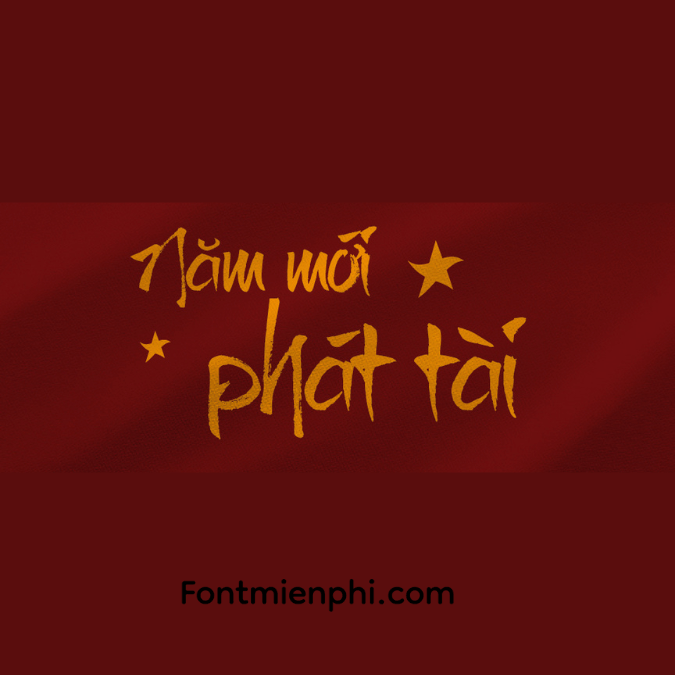
Việt hóa font UTM Brushtip-C ,font Tết
Việt hóa font UTM Brushtip-C
Mô tả font UTM Brushtip-C và font Tết
1. UTM Brushtip-C: Font UTM Brushtip-C là một kiểu chữ viết tay, mang đến cảm giác tự nhiên và thoải mái. Với các nét chữ mềm mại, font này thường được sử dụng trong thiết kế đồ họa, quảng cáo, và các sản phẩm liên quan đến nghệ thuật. Font có khả năng thể hiện sự sáng tạo và cá tính, phù hợp cho các dự án cần tăng tính thẩm mỹ.
2. Font Tết: Font Tết được thiết kế đặc biệt để phù hợp với không khí của dịp Tết Nguyên Đán. Nó thường mang các yếu tố truyền thống, như hình ảnh hoa mai, hoa đào, hoặc các biểu tượng phong thủy. Kiểu chữ này thường được sử dụng trong thiệp chúc Tết, banner quảng cáo, và các sản phẩm văn hóa trong dịp lễ hội.
Ứng dụng
• UTM Brushtip-C: Thích hợp cho các sản phẩm sáng tạo, quảng cáo hoặc in ấn mang tính chất nghệ thuật.
• Font Tết: Thích hợp cho các sản phẩm liên quan đến Tết, như thiệp chúc mừng, trang trí không gian lễ hội.
Kết luận
Cả hai font đều mang đến những giá trị thẩm mỹ riêng biệt, giúp truyền tải thông điệp một cách hiệu quả và hấp dẫn hơn.